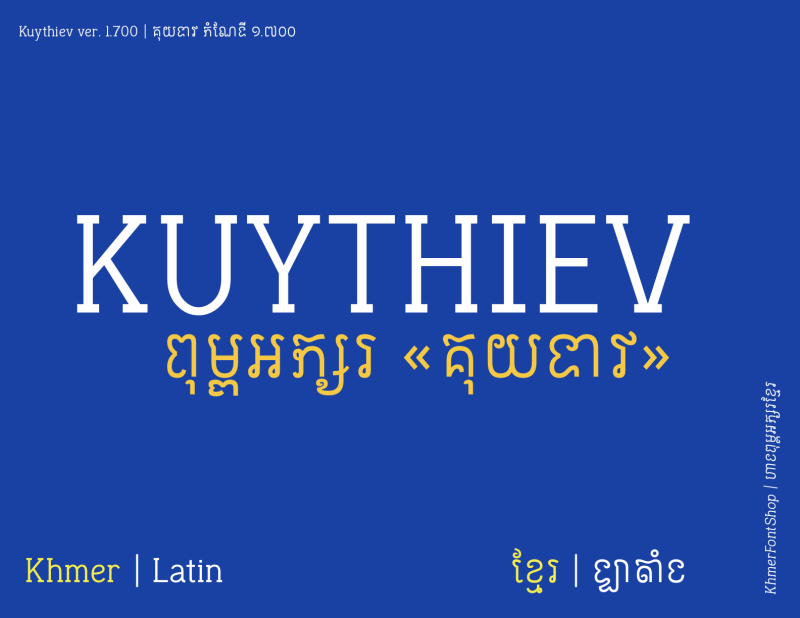
Traditional san serif style 'Aksar Kham' Khmer Font with slab serif style Latin in Regular and Italic form
Kuytiev គឺជាពុម្ពអក្សរ Opentype ដែលប្រើបាននៅក្នុងផលិតផលសូហ្វវែរកុំព្យួទ័រជាច្រើនប្រភេទដែលគាំទ្រ OTFs។ ប្រើក្នុងការរចនាផលិតផល ផ្លាកយីហោ ឡូហ្គោ ក្រាហ្វិក ទីផ្សារ ឬគ្រប់ទីកន្លែងណាដែលអ្នកអាចបញ្ចូលភាសាខ្មែរ។ Kuytiev ត្រូវបានបង្កើតឡើងដើម្បីផ្តល់នូវរូបរាងទាន់សម័យនិងអារម្មណ៍ដល់អក្សរមូលបុរាណរបស់កម្ពុជាយើងដែលនៅតែរក្សានូវទ្រង់ទ្រាយដើមនៃទម្រង់អក្សរនីមួយៗ។ នេះគឺជាការស្វាគមន៍បែបទំនើបនៃរចនាបថមុទ្ទវិទ្យាខ្មែរថ្មីដែលបញ្ចេញម៉ូដអក្សរខមជាពិសេស។
Kuytiev is an Opentype font that can be used in a variety of computer software products that support OTFs. Use it in product designs, branding, logos, graphics, marketing, or anywhere you can type in Khmer. Kuytiev was created to give a modern look and feel to our classic Moul script yet retaining the original shape of each letter form. This is a modern welcome of a new style of Khmer typography that features the Kham script.